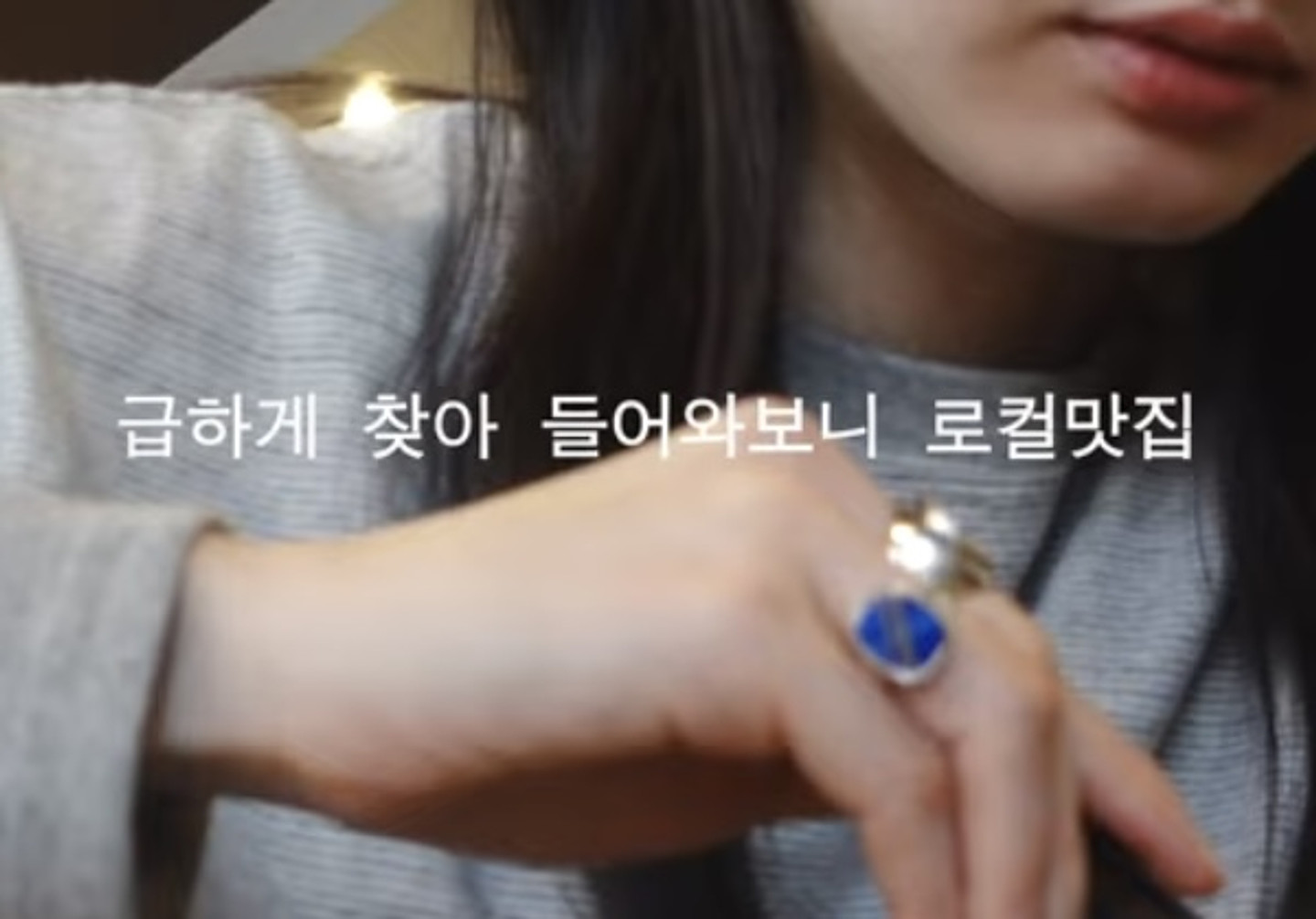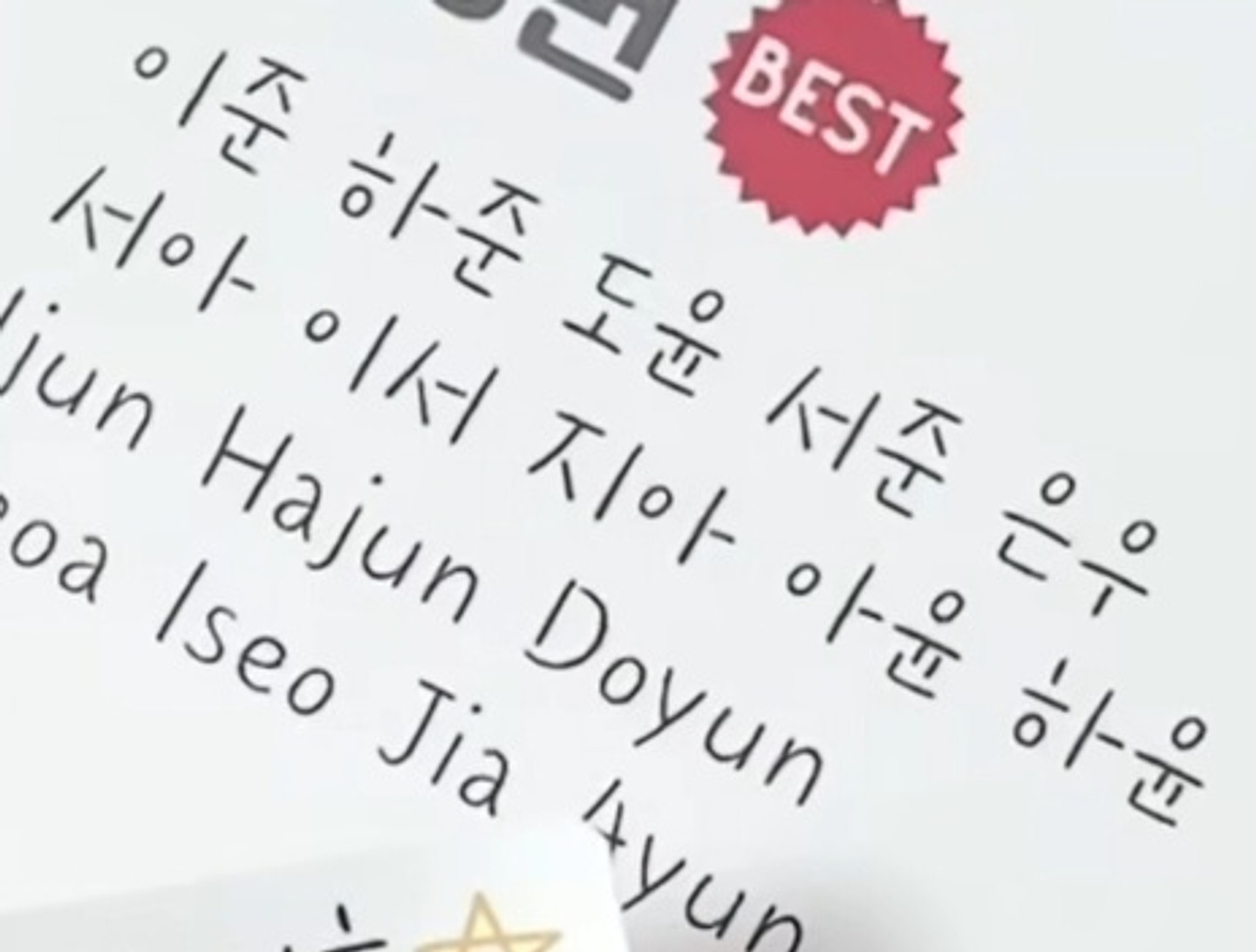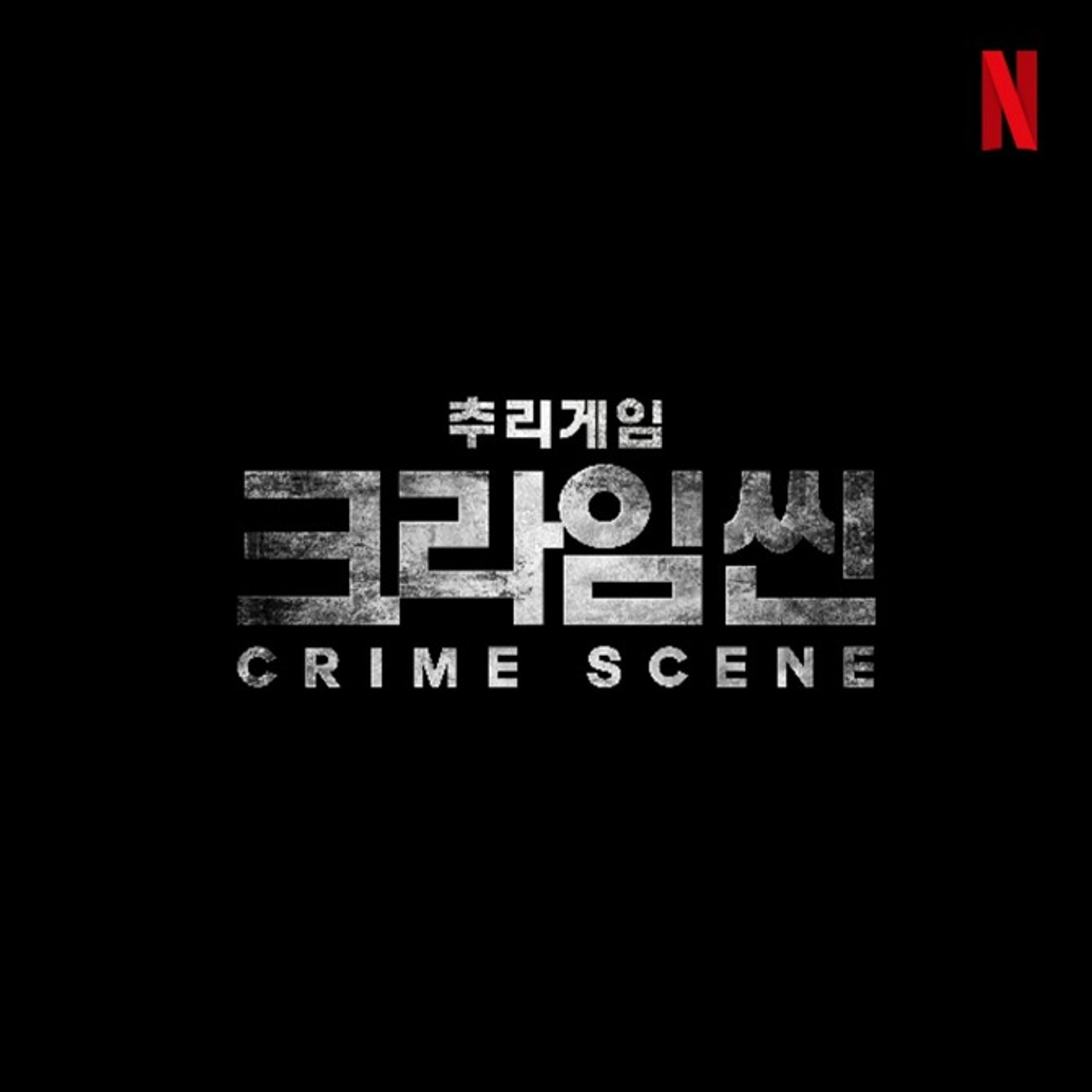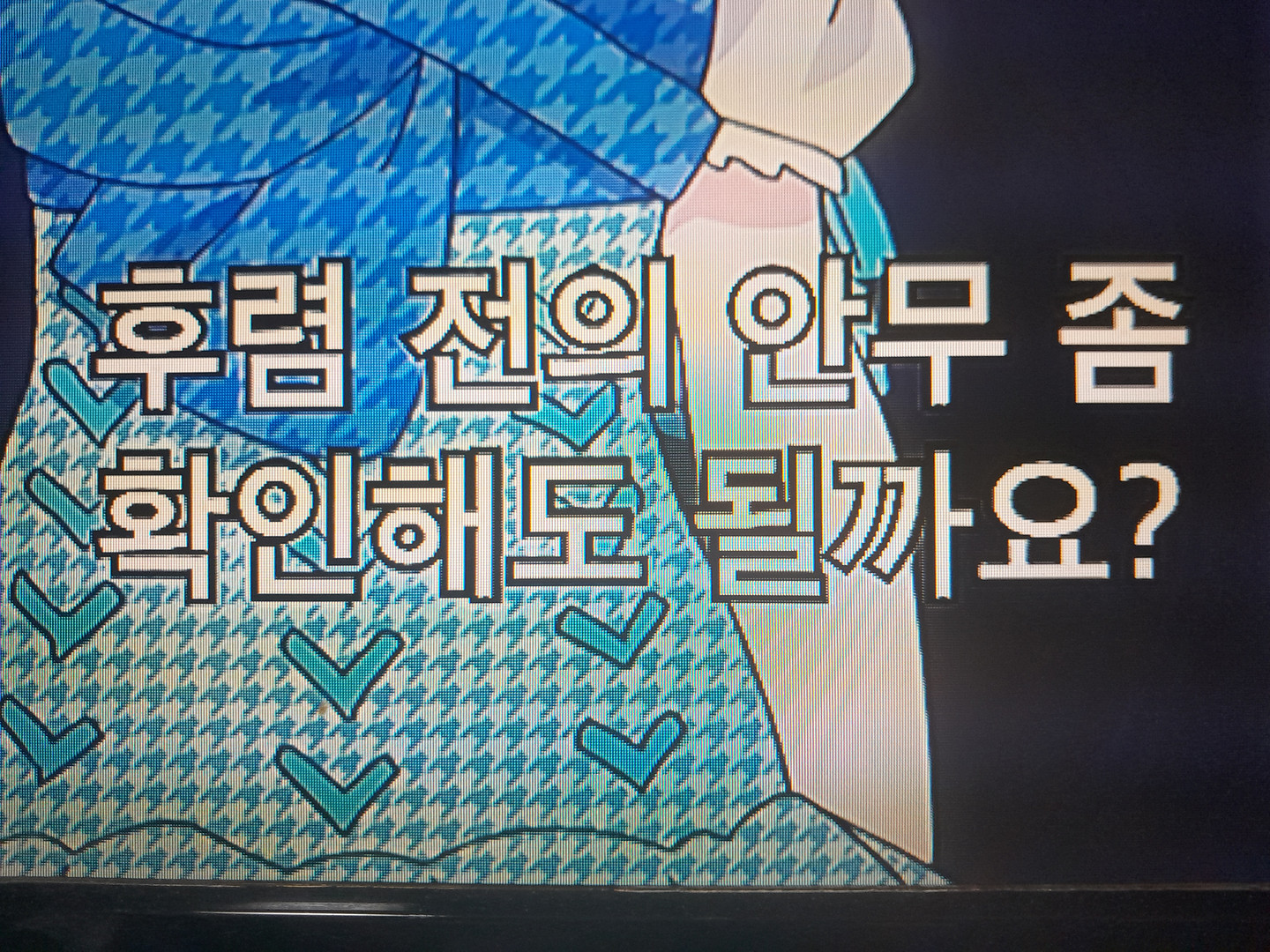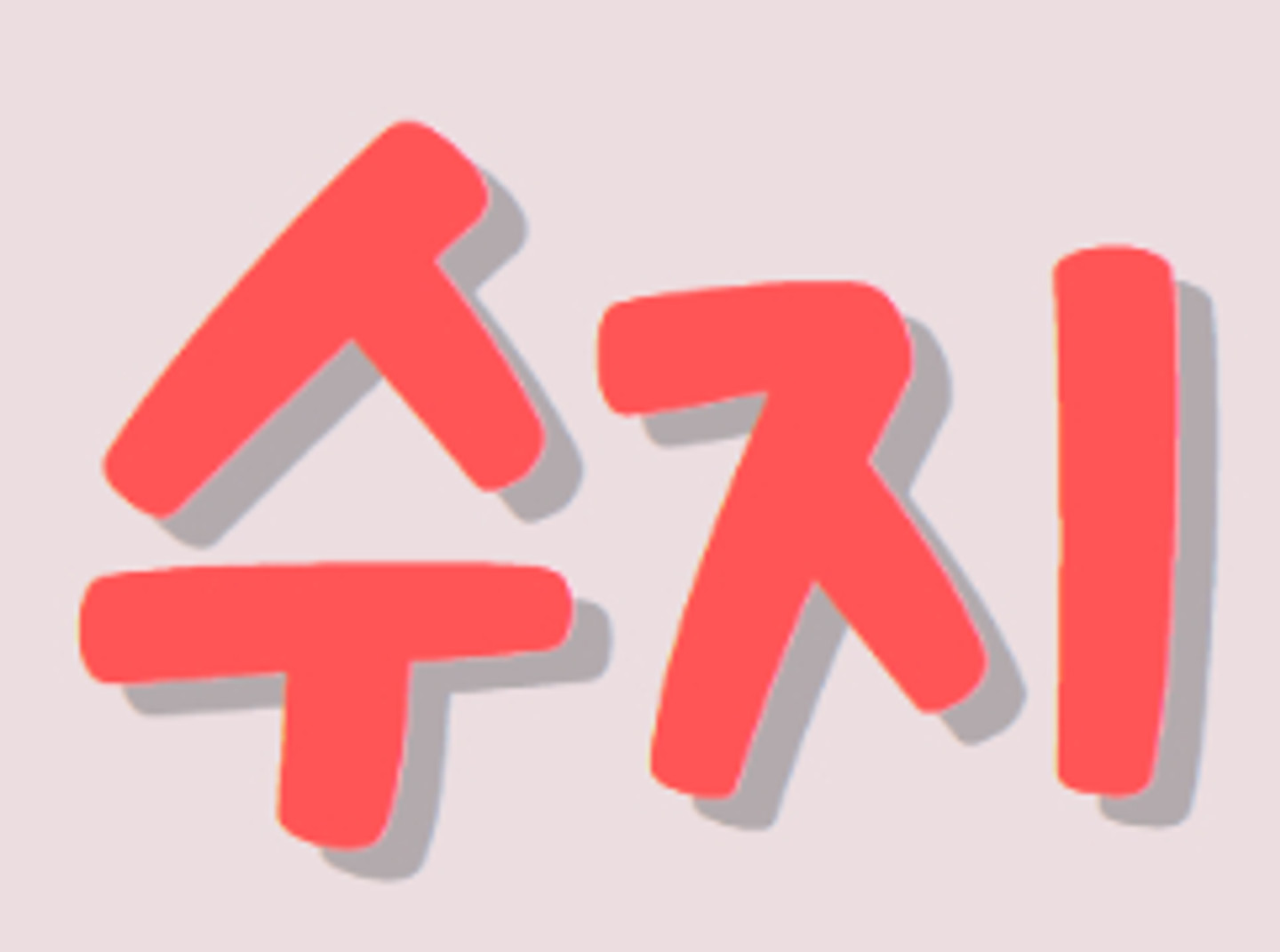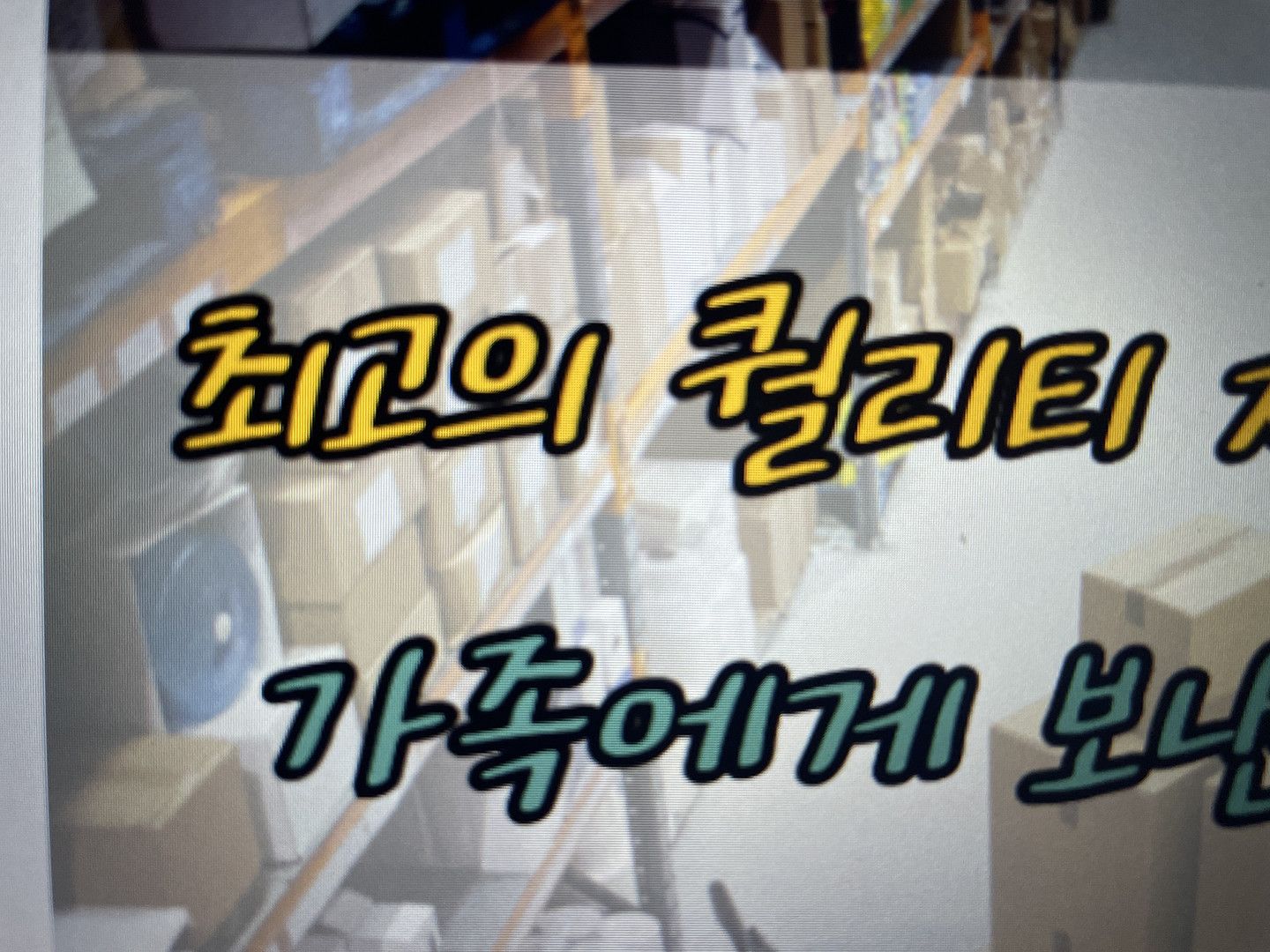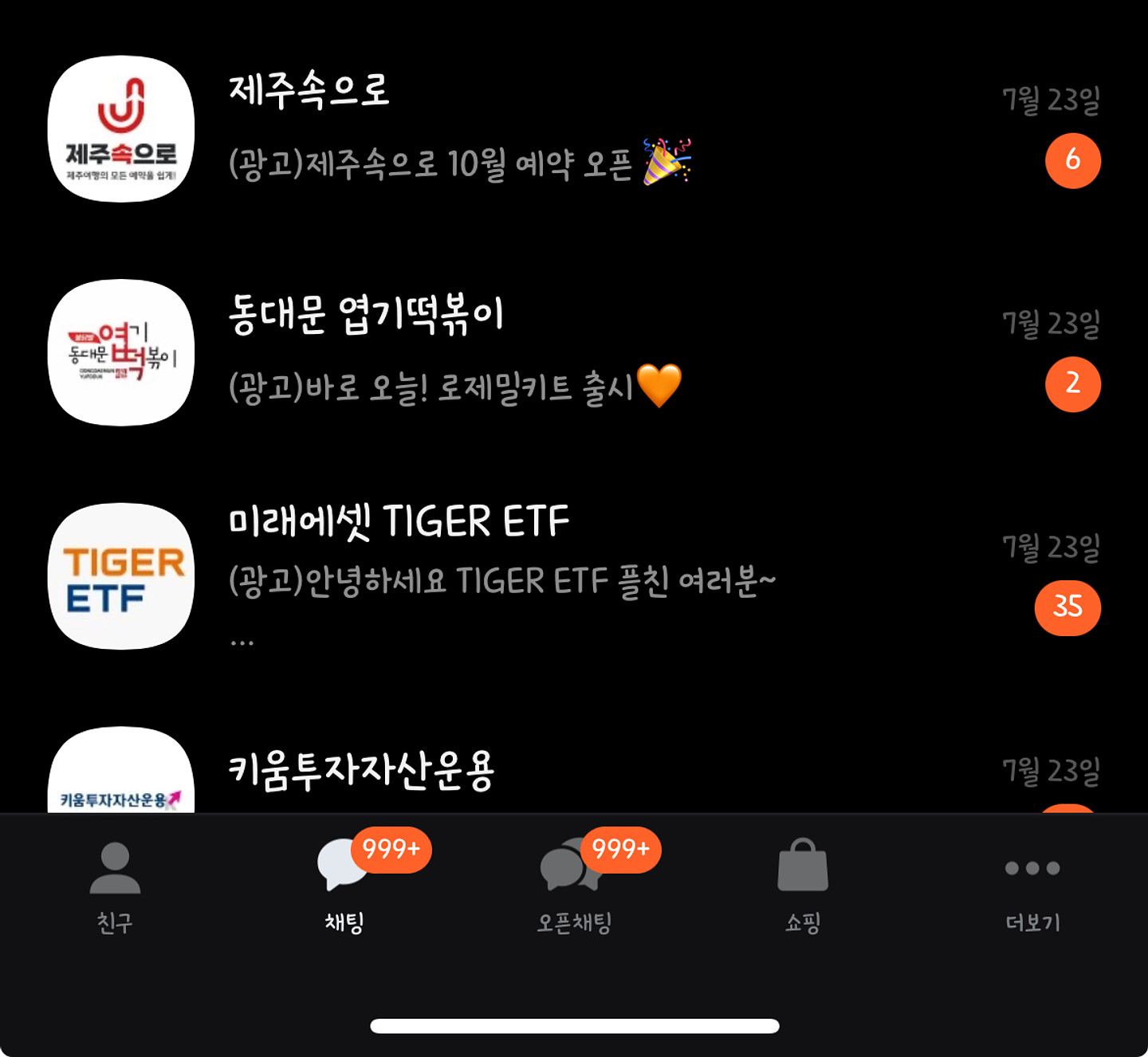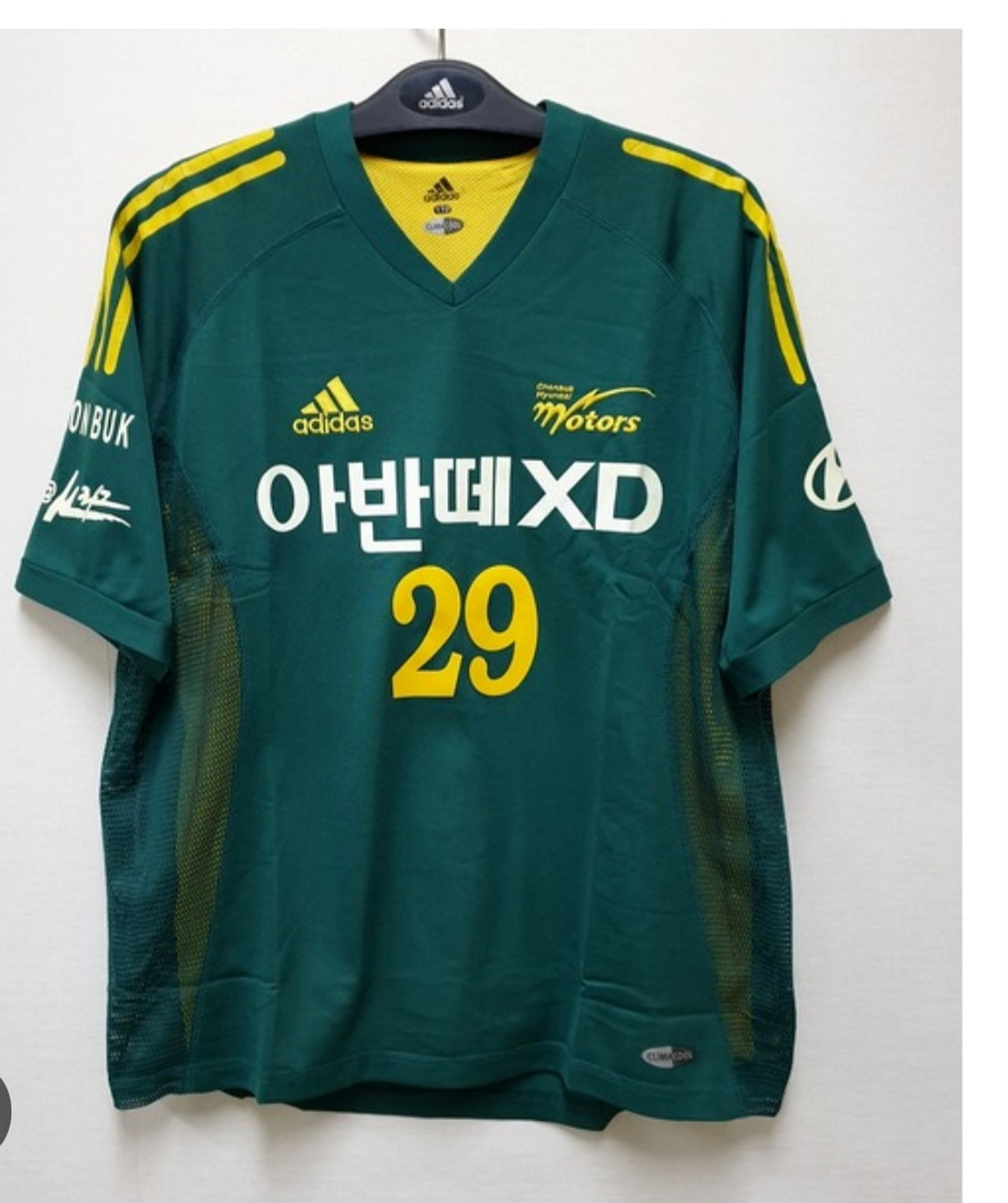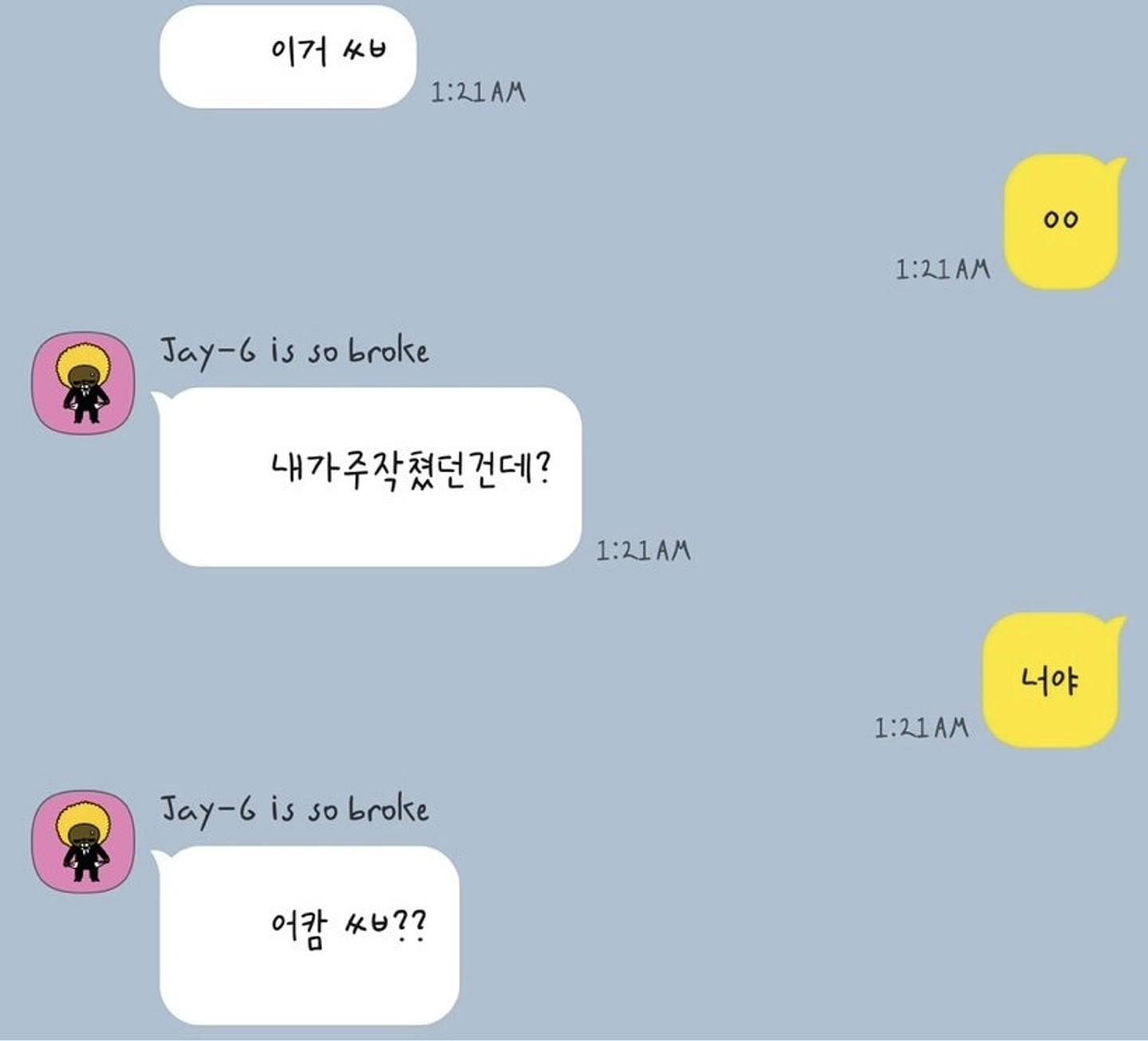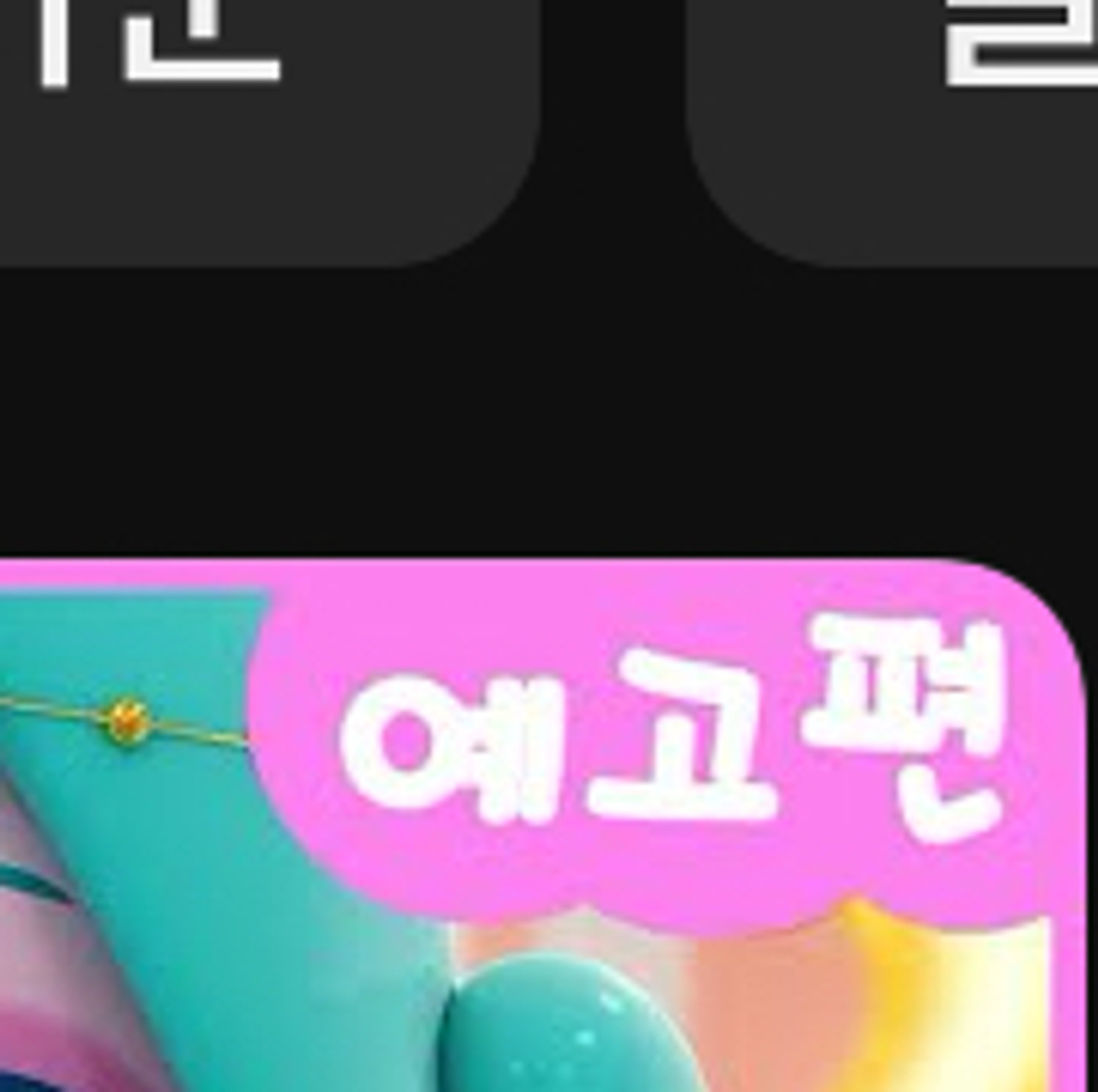
이 폰트 궁금해요
이름이 뭘까요ㅠㅠ 따로 그린건지 폰트가 있는건지 모르겟습니다
폰트 정보 아시는 분 ㅠㅠ 다 비슷 비슷해보이는데 ㅁ 이나 가로 세로 길이감이 달라서 정확한 폰트 찾기가 어려워용
이거 폰트가 궁금합니다 !!!! ㅠ
폰트
1인당 10만원, 4인 가족이면 40만원! < 여기 부분 글씨체 뭘까요 .....
폰트 이름이 궁금합니다
이 글씨체 알려주세요
폰트 이름 아시는 분 ㅠㅠ
무슨 폰트인지 아시는분 계실까요?
폰트고수집 알려주세요..
이 예쁜 폰트를 찾아주세요..
이거 무슨폰트인 지 아시는 분 계실까요 ㅠㅠㅠ?
비슷한 폰트라도 뭐가 있을가요?
이게 무슨 폰트일까요?
이 로고에 들어간 서체 좀 알려주세요ㅠㅠ
자막 템픍릿 50종이 있으니까 이 꾸불꾸불 글씨 폰트가 뭔가요 ..?
글씨 폰트들 궁금합니다
이 폰트가 궁금해
해당폰트가 어떤폰트일까요 같은서체를 못찾겠습니다. 도움부탁드려요 👏
폰트 알려줘
이런 숫자나오는 폰트 알려주세요 ㅜ
폰트 정보 부탁드려요 감사합니다!!
“서초클래스 홍익표” 모두 같은 폰트 같은데, 어떤 폰트인가요??
메인 전국생활체육대축전 글자 폰트가??? 뭘까요
자막에 “진짜?”에 쓰인 폰트가 궁금합니다
고딕체 같은데 도저히 뭔지 모르겠어요 ㅜㅜ 도와주세요!
이 폰트 이름이 뭔가요
이건 무슨폰트인가요?
무슨폰트인지 부탁 좀 드립니다 감사합니다.
베테랑 포스터에 쓰인 폰트 숫자랑 한글이랑 서로 다른 폰트면 숫자만 알려주세요 ㅠㅠ
베테랑 포스터에 쓰인 이 폰트 무엇인가요 ㅠㅠ
폰트 이름 부탁드려요
폰트 알 수 있을까요? ㅜㅜ
요 폰트 하찮아보여서 넘 귀여운데 뭐인가요 ㅠㅠㅠㅠㅠㅠㅠ
어떤 연예인이 인스타스토리에서 사용한 폰트인데 찾을 수가 없네요.
안녕하세요 고수님들 ㅠㅠ 이 폰트가 뭘까요 ㅠㅠ 제발 자비를 베풀어 주세요 ㅠㅠ
폰트가 궁금합니다!
이거폰트 알수잇을까요 ㅠㅠ
무슨 글꼴 일까요?
띠순이매거진 계정의 이 폰트 이름 뭔가요.?? 2시간 째 찾았는데 모르겠네요 도외주세요ㅠㅠ
지붕 뚫고 하이킥에 나온 폰트 알려주세요
이거 무슨 폰트인가요???🥹
영어 폰트 같은데 찾아봐도 모르겠네요
도톰하고 글씨 예쁜데요. 이 폰트 뭘까요? 아래 링크에서 봤습니다. 알려주시는 분 복받으실 거예요. 어린 양에게 자비를 베풀어주세요. https://youtube.com/shorts/07WBvh8e9Xg?si=CQoBsQLXChDySbtV
손글씨같은 폰트 궁금해요
아기
손글씨 느낌
괴담출근에 나왔던 폰트인데 이 폰트 아시는분 계신가요ㅠㅠ
어느 유튜버의 특정 장면에서 본 글입니다. 무슨 폰트인지 궁금하네요! ^L^
무슨 폰트일까요? 네이버 블로그 글이었습니다.
폰트 이름알려주세요
이거 무슨 폰트일까용?
선거 포스트에 많이 쓰이는 글씨체인데 나눔스퀘어랑, 본고딕과 비슷한거 같은데 똑같지는 않아서 질문 올립니다. 답변 부탁드릴게요.